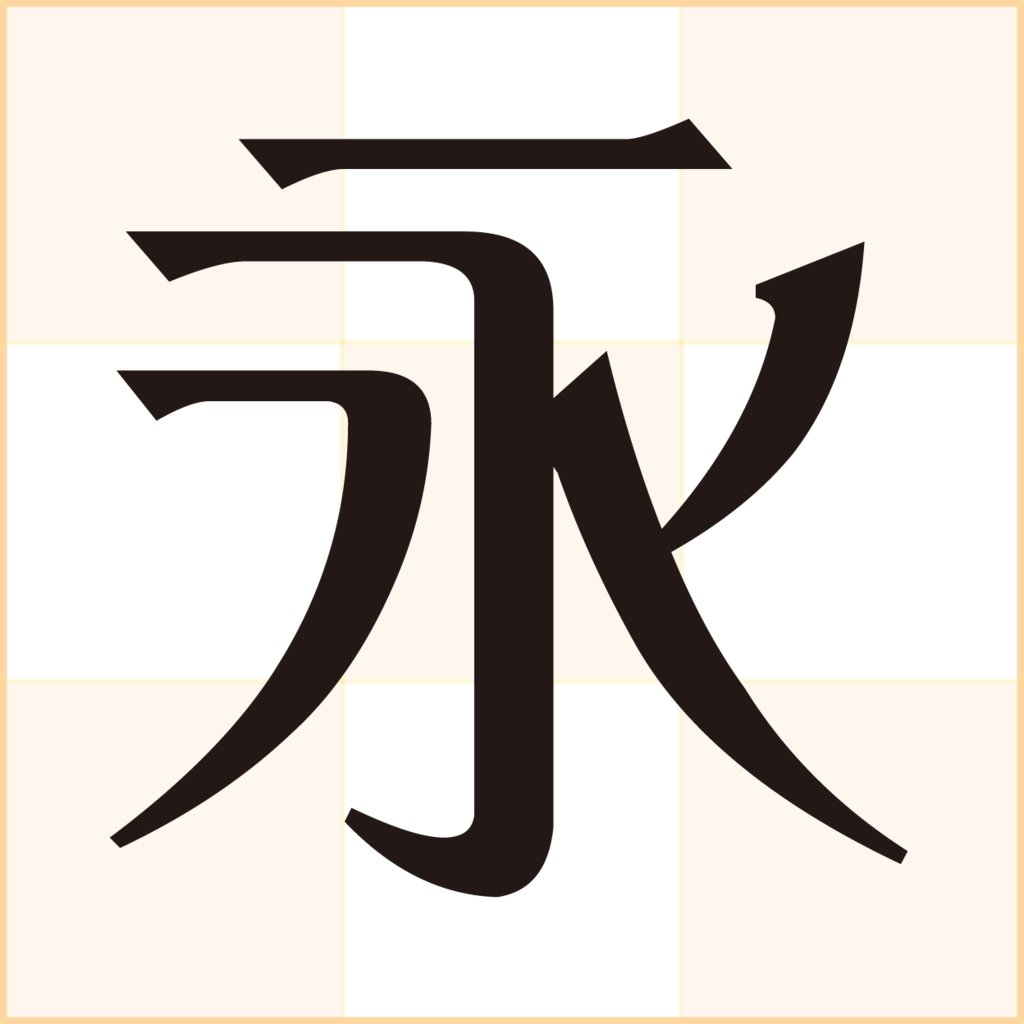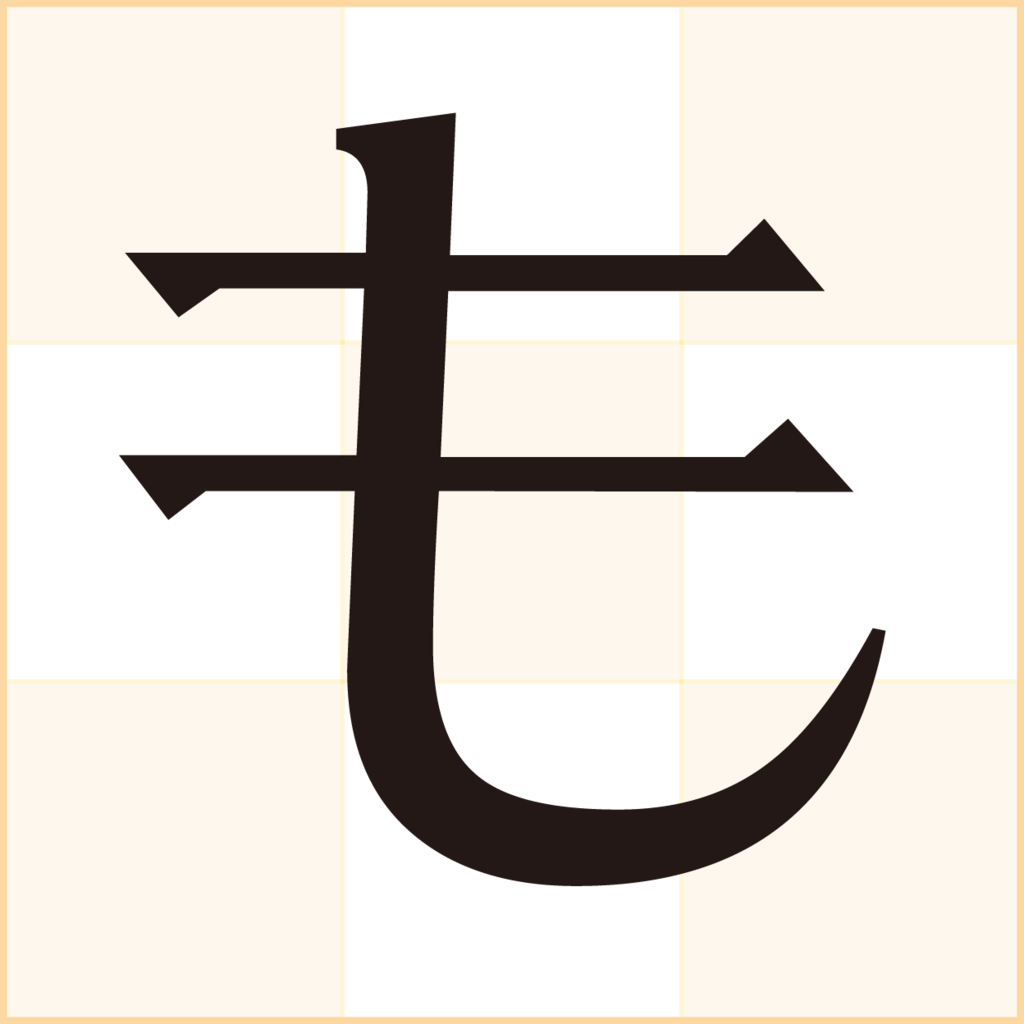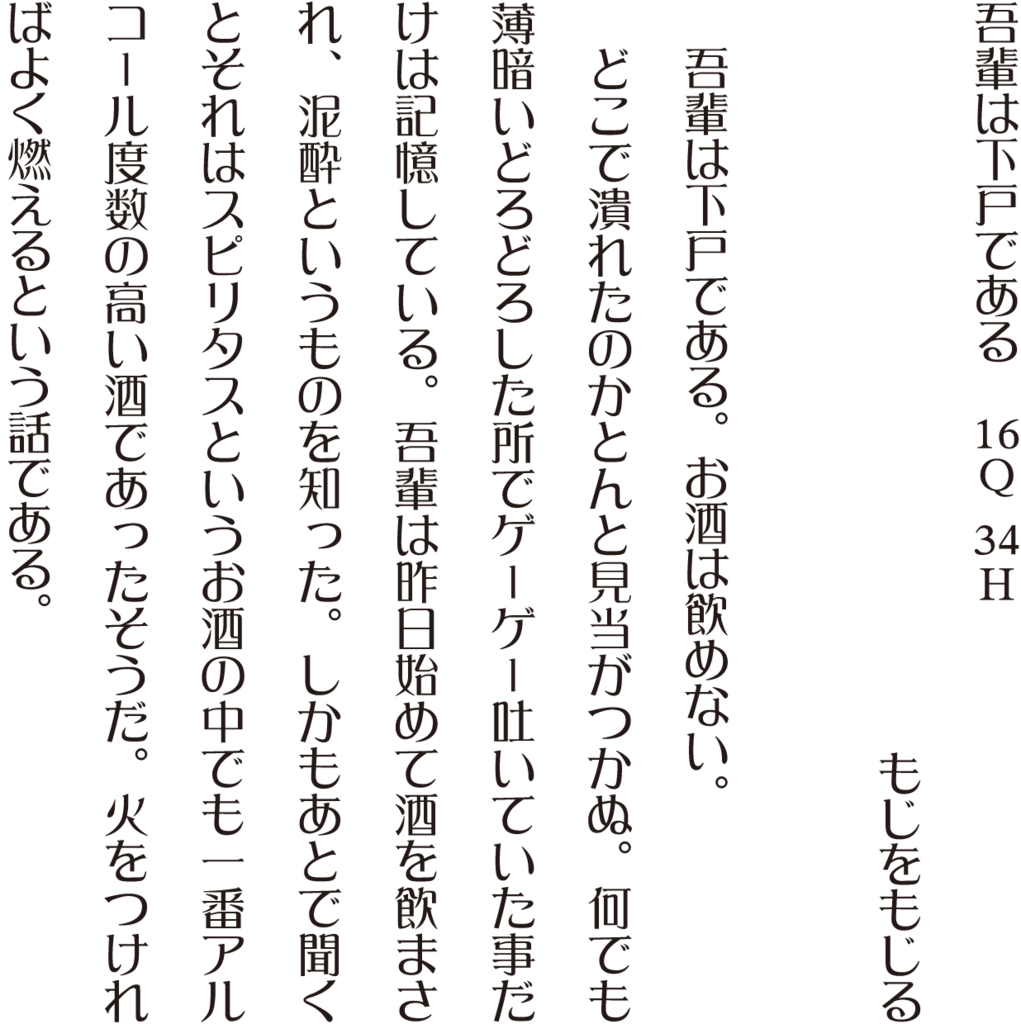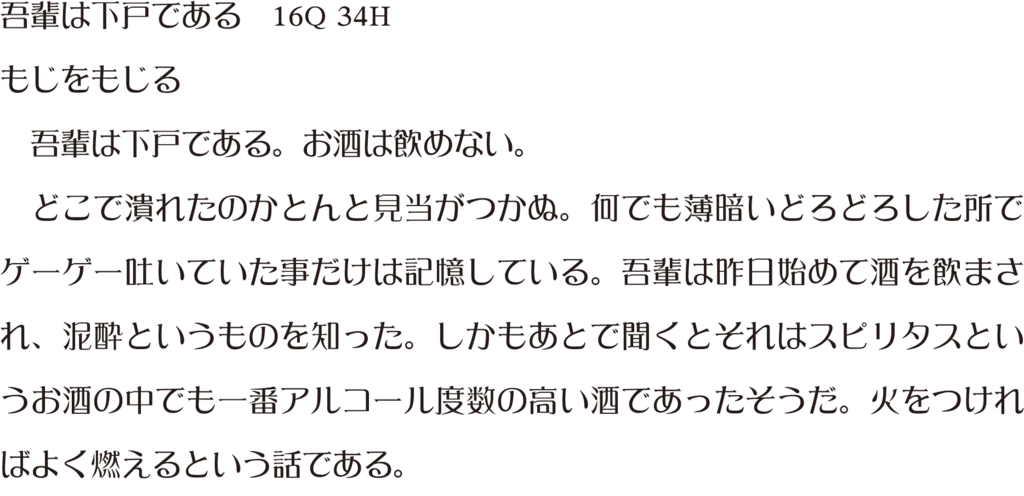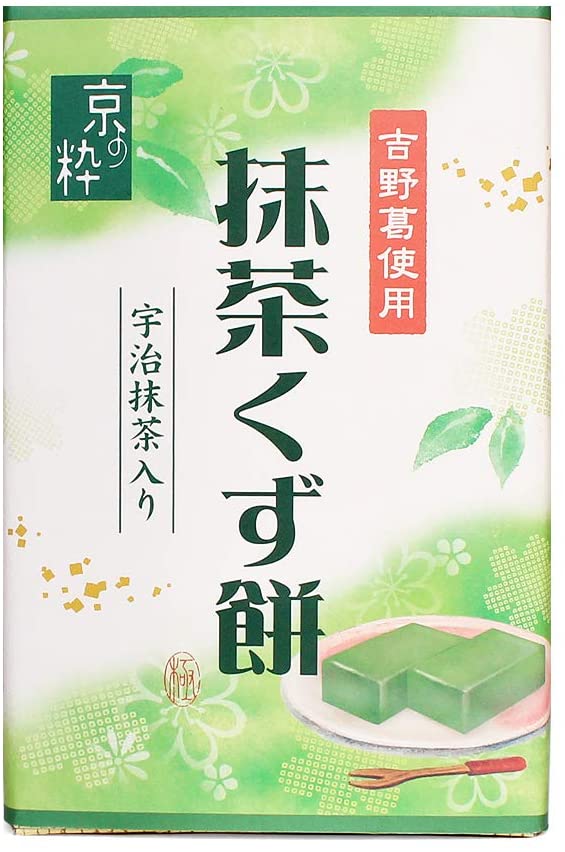
麗雅宋
明朝体をベースに真四角なイメージをもたせた書体。麗雅宋の和文用仮名は「有限会社 字游工房」が制作している。
麗雅宋の組見本(W5)
新元号「令和」麗雅宋書体見本
新元号「令和」の麗雅宋の書体見本。
サッポロ一番「カップスター」シリーズの文字に麗雅宋が採用
サンヨー食品株式の「サッポロ一番」ブランドにて発売されているカップラーメン「カップスター」シリーズの文字に麗雅宋が採用されている。
宇治安「抹茶くず餅」の文字に麗雅宋が採用
宇治安の「抹茶くず餅」の文字に麗雅宋が採用されている。